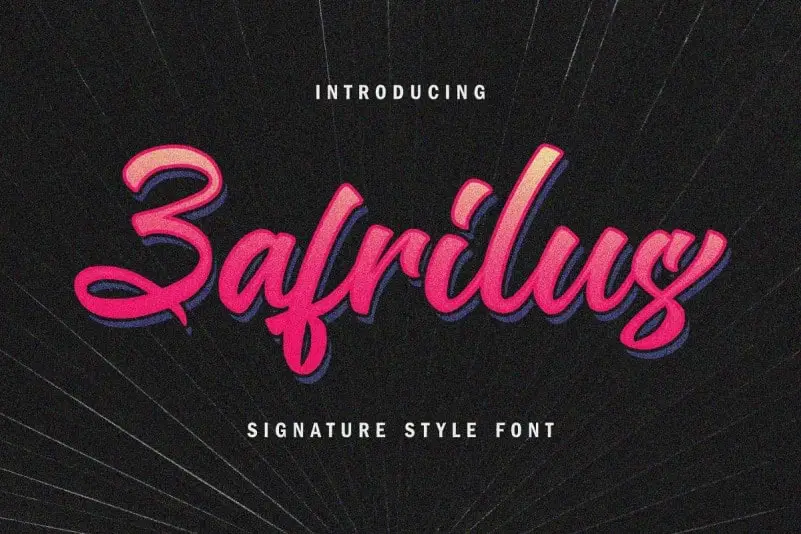
Zafrilus Bold Script Font – Fonte Grátis
Zafrilus Bold Script Font
Introduzimos Zafrilus Bold Script Font, uma nova fonte tipográfica de estilo script com letras afiadas e belas que criam fontes vintage, trendy e elegantes. Esta fonte é perfeita para dar um toque moderno a qualquer projeto visual, seja em revistas digitais ou em cartões de visita personalizados. Ideal tanto para textos formais quanto para gráficos divertidos e coloridos, Zafrilus Bold Script é uma escolha inteligente para quem busca se destacar no mercado da design editorial. Suas linhas rígidas combinadas com um toque delicado das letras garante a ela um ar vintage elegante que atingirá qualquer público-alvo desejável. O designer 99designs criou Zafrilus Bold Script, uma fonte de estilo script robusta e moderna. Essa descoberta vem em um momento ideal para quem busca se diferenciar na era digital do design gráfico, oferecendo uma combinação inovadora e sofisticada que traz um toque vintage e atemporal às criações digitais. Zafrilus Bold Script é perfeitamente adaptável a diferentes formatos de mídia. Seja para usar em websites, gráficos ou mesmo aplicativos móveis, esta fonte mantém seu design único e versátil que combina o tradicional com o moderno, tornando-a uma excelente escolha para qualquer designer interessado em inovar e se destacar no mundo dos recursos visuais.